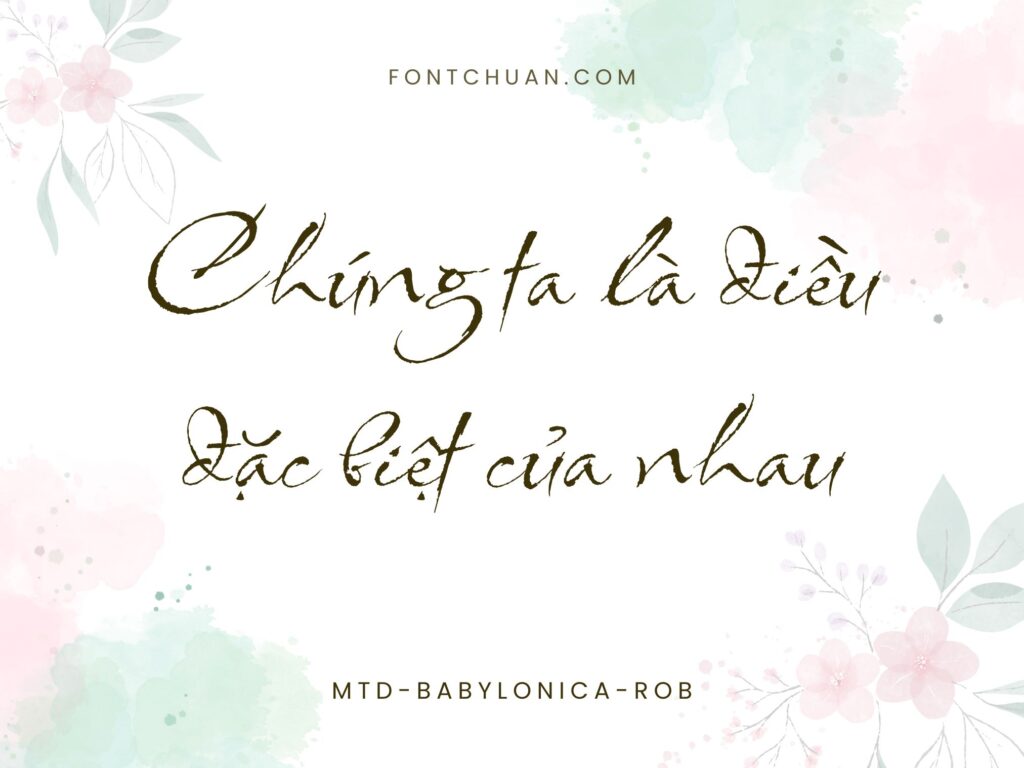
Font MTD Babylonica Rob Việt Hóa
Tác giả Font: Typesetit
Babylonica Rob là một font chữ độc đáo được thiết kế bởi Typesetit, mang phong cách Font chữ thư pháp mềm mại và tinh tế. Với đường nét uốn lượn nhẹ nhàng, font này tạo cảm giác thanh lịch và nghệ thuật, phù hợp với nhiều loại thiết kế sáng tạo. Để hỗ trợ cộng đồng thiết kế Việt Nam, Mộc Hạ đã Việt hóa font Babylonica Rob, giúp font này tương thích hoàn toàn với tiếng Việt cùng hơn 200 ngôn ngữ khác. Font Babylonica Rob Việt hóa đã được thành viên Font Chuẩn sưu tầm và đăng tải, nhằm giúp các nhà thiết kế có thêm lựa chọn phù hợp với nhu cầu sáng tạo.
Về đặc điểm thiết kế, Babylonica Rob sở hữu các đường nét uyển chuyển, mang lại cảm giác mềm mại nhưng vẫn giữ được độ sắc sảo. Các ký tự được thiết kế với độ tương phản vừa phải, giúp tăng tính thẩm mỹ và dễ đọc trong nhiều trường hợp sử dụng. Font này đặc biệt phù hợp cho các thiết kế thiệp cưới, thương hiệu cao cấp, typography nghệ thuật và các dự án sáng tạo. Ngoài ra, Babylonica Rob cũng thích hợp cho các ngành nghề như quảng cáo, giáo dục và sự kiện, giúp mang đến phong cách sang trọng và thu hút.